Как различить строчные «к» и «н» в рукописном шрифте
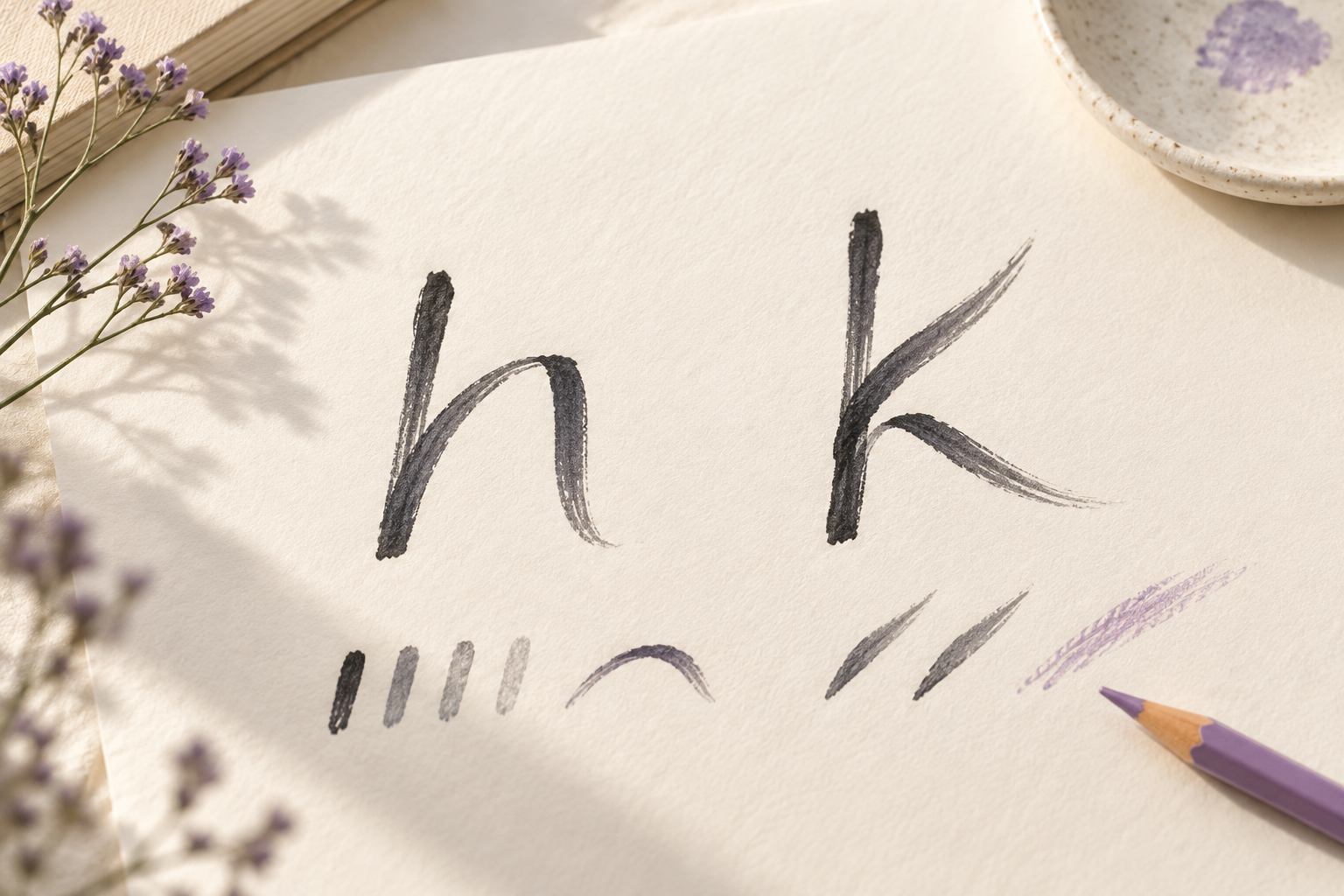
Строчные «к» и «н» в рукописном шрифте легко сблизить, если обе буквы построены вокруг похожих вертикальных штрихов. Чтобы читатель не угадывал слово, задайте им разные конструкции: у «н» сделайте ясную систему стойки и перекладины, а у «к» — заметное место соединения диагонали с основной частью. Затем проверьте пару в соседстве, в словах и в уменьшенном размере: отличаться должен не один эффектный штрих, а общий силуэт и движение пера.
Сначала сравните не названия, а траектории пера
При рисовании пары полезно на время забыть, как выглядят печатные образцы. Начните с движения руки. У «н» обычно есть две стойки и перекладина между ними; конструкция читается как собранная рамка или арка. У «к» есть основная стойка и боковая часть, расходящаяся от точки соединения: диагональ ведёт взгляд в сторону, а не просто замыкает пространство между двумя вертикалями. В рукописном варианте эти схемы могут быть свободными, но направления движения остаются хорошей опорой.
Нарисуйте каждую букву одним непрерывным жестом так, как вы действительно собираетесь её писать. Не исправляйте формы до анализа: сначала отметьте начало, направление, места смены движения, точки соединения и выходной штрих. Если обе буквы получились одной петлёй с похожим верхом, дело не обязательно в слабом рисунке. Скорее, выбранная траектория не дала им достаточно разных конструктивных событий. Попробуйте изменить порядок штрихов или поднять точку ответвления у «к».
Для диагностики достаточно листа и контрастного инструмента. Нарисуйте по несколько вариантов пары с одинаковой высотой и толщиной, чтобы сравнивать именно конструкцию. Подпишите варианты на отдельном листе, а сами знаки перемешайте: так проверяющий не будет видеть подписи и не станет читать их по ожиданию. Попросите другого человека назвать буквы без подсказки. Если он уверен только в знакомых словах, различие пока держится на контексте, а не на форме.
Настройте «н»: перекладина должна принадлежать именно ей
Сначала зафиксируйте пропорции строчной «н». Выберите высоту и ширину корпуса, расстояние между стойками, характер перекладины и место её поворота. Важно не копировать механическую схему: связное письмо может округлять углы, наклонять опоры и сглаживать переходы. Но даже мягкая форма должна давать понятный маршрут взгляда: подъем по первой стойке, переход через верх или середину, спуск по следующей опоре. Читателю нужна непрерывная логика, а не геометрическая идеальность.
Если перекладина слишком низкая, слишком короткая или сливается с выходным штрихом, «н» может выглядеть как две почти параллельные палочки. Если она чрезмерно высокая, буква начинает напоминать связку отдельных дуг. Подберите положение на уровне соседних строчных: сравните высоту верхнего соединения с арками других букв и посмотрите, не проваливается ли внутренняя белая область. Это полезнее, чем оценивать перекладину отдельно от корпуса.
Проверьте, различает ли «н» вход и выход. Входной штрих может прийти снизу слева, а выходной уйти вправо, но не позволяйте им случайно стать дополнительной стойкой. Частая ловушка — длинный соединительный выход, который возвращается к корпусу и создаёт похожую на диагональ «к» линию. Упростите соединение, перенесите его к базовой линии или измените угол, чтобы перекладина оставалась единственным сильным поперечным жестом.
Настройте «к»: покажите место ответвления
У «к» читатель ищет не перекладину, а точку, где боковые штрихи отходят от основной стойки. Сделайте это место конструктивно убедительным. Ответвление может находиться выше середины, около неё или ниже — выбор зависит от общей пластики алфавита. Главное, чтобы ветви не возникали как случайные короткие засечки и не продолжали стойку так, будто перед нами «н». Нарисуйте одну версию с более ранним ответвлением и одну с более поздним, затем поставьте их рядом с другими буквами.
Верхняя диагональ и нижняя ножка не обязаны быть одинаковыми. Их длина и угол определяют баланс: чрезмерно длинная верхняя линия делает знак острым и тяжёлым, а короткая нижняя может исчезнуть при уменьшении. Однако симметрия сама по себе не цель. Если ваш почерк выразителен разной длиной движений, сохраните это качество и обеспечьте различие через точку соединения, открытое пространство и силуэт.
Избегайте «склейки» в узле. Когда несколько линий сходятся в одной тесной точке, она темнеет, и вместо ясной развилки получается пятно. Разведите начала ветвей на небольшое расстояние по стойке или измените последовательность движений, чтобы контуры не пересекались. Если рукописная логика требует одного узла, оставьте вокруг него достаточно белого пространства. При сборке цифрового контура проверьте, не закрывается ли этот просвет из-за слишком жирного соединения.
Разведите силуэты и внутренние просветы
Сравнивайте не только чёрные линии, но и пустоты между ними. У «н» внутри корпуса обычно возникает широкое окно или пара открытых просветов; у «к» пространство раскрывается вбок вокруг места ответвления. Если обе внутренние области похожи по форме и размеру, поменяйте одну конструкцию. Например, сделать «н» более арочной, а «к» — более угловатой; или оставить «н» компактной и собрать у «к» явную боковую развилку. Выберите один-два признака и удерживайте их во всех вариантах, вместо того чтобы каждый раз менять всё сразу.
Итог: закрепите для пары один визуальный якорь
Различимость «к» и «н» появляется из конструкции и сохраняется, когда она видна в общем силуэте, соединениях и словах. Определите характер перекладины «н» и место ответвления «к», выберите для каждой формы постоянный признак и проверьте его при разных размерах. Когда пара перестаёт требовать угадывания, можно переносить найденное правило на остальные буквы и собирать шрифт дальше.